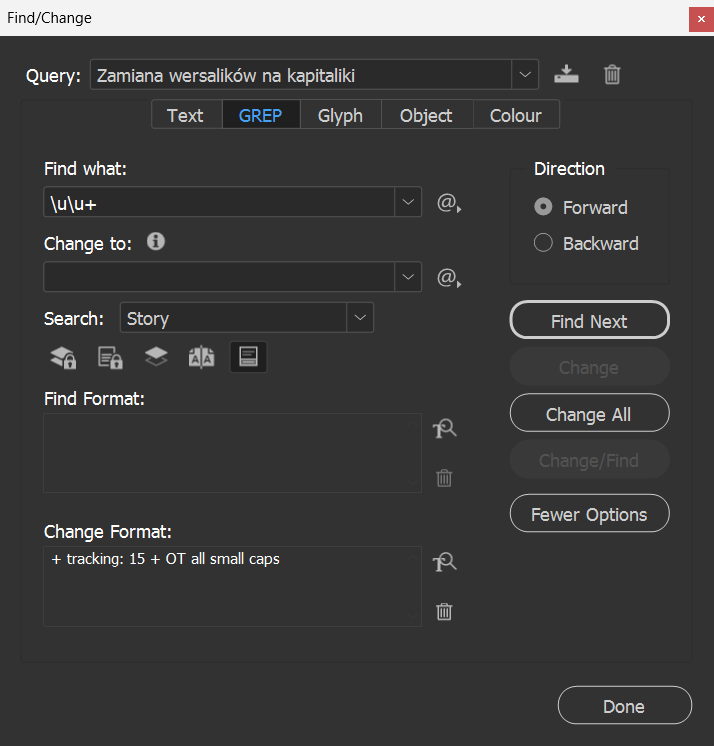
Dobry skład tekstu
1. W pro­ce­sie składu tek­stu pole­gajmy na wła­snej oce­nie optycz­nej całej pracy. Nie kie­rujmy się jedy­nie auto­ma­tycz­nymi usta­wie­niami tek­stu w apli­ka­cjach do składu.
2. Naj­waż­niej­szym narzę­dziem skła­da­cza jest wprawne i kry­tyczne oko.
3. Dbajmy o kon­se­kwen­cję składu, czy­tel­ność i łatwość czy­ta­nia.
4. Naj­pięk­niej­szy skład jest wtedy, gdy uży­wamy w dziele jed­nego boga­tego kroju pisma (maks. 2), upew­nijmy się zatem, że wybrany krój posiada wszyst­kie nie­zbędne dla danego składu formy gra­ficzne zna­ków (np. kur­sywę, kapi­ta­liki, frak­cje Open­Type).
5. Gdy w tek­ście uży­wamy wer­sa­li­ków, sto­sujmy cyfry regu­larne.
6. Gdy w tek­ście uży­wamy kapi­ta­li­ków, sto­sujmy cyfry nautyczne.
7. Ogra­ni­czajmy rów­nież liczbę stopni pisma w dziele.
8. Zasada ​„im mniej tym lepiej” w skła­dzie spraw­dza się w stu procentach.
Poni­żej przed­sta­wiam kod GREP na zamianę wer­sa­li­ków na kapitaliki:
Znajdź: \u\u+
Zamień: pusto
Zmień for­mat: Kapi­ta­liki z roz­świe­tle­niem 15tys. firetu